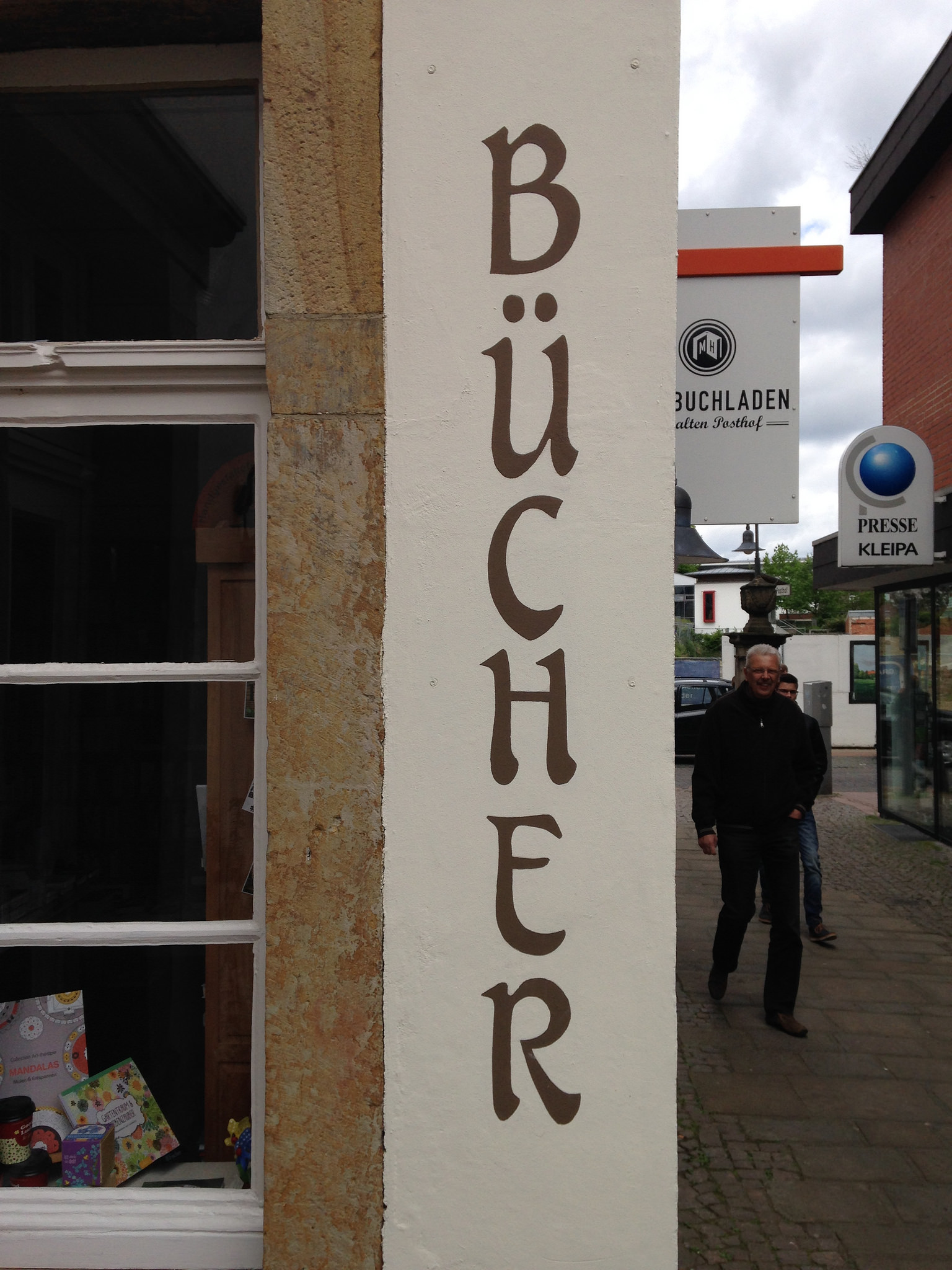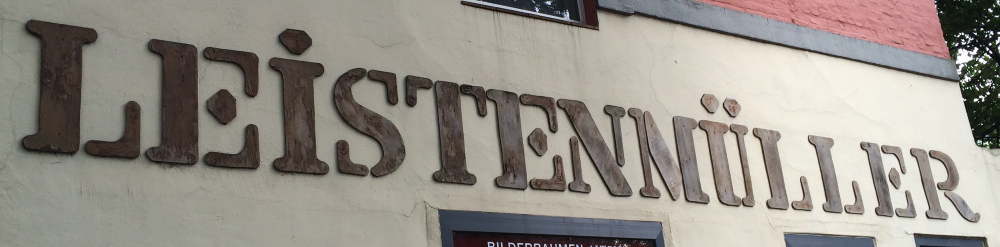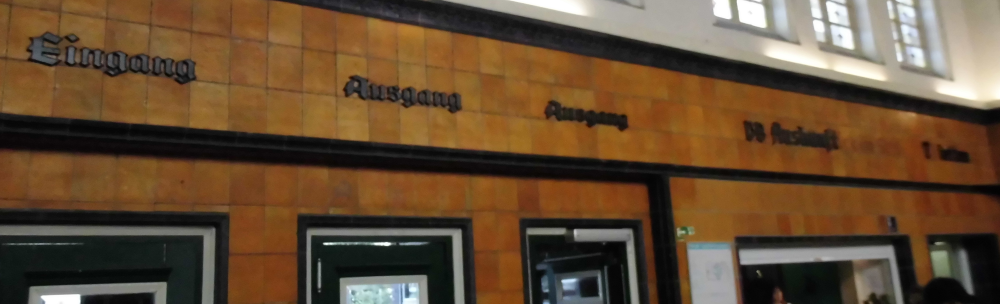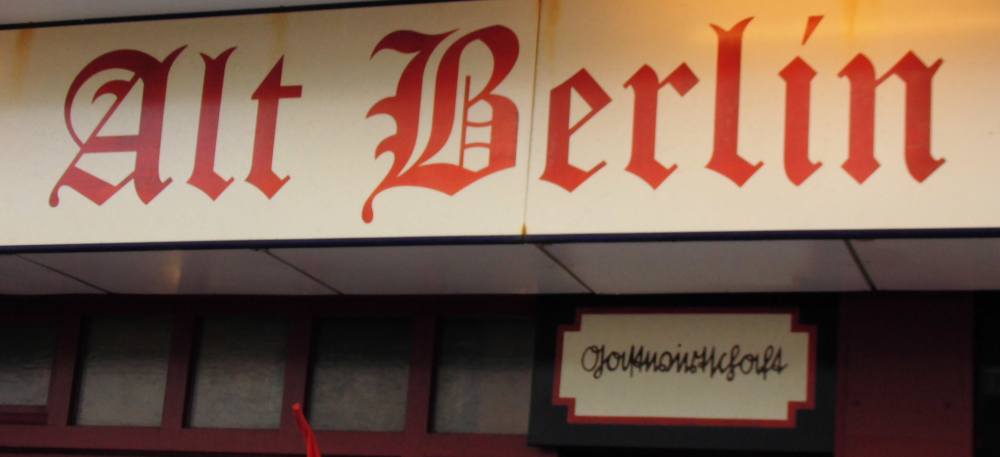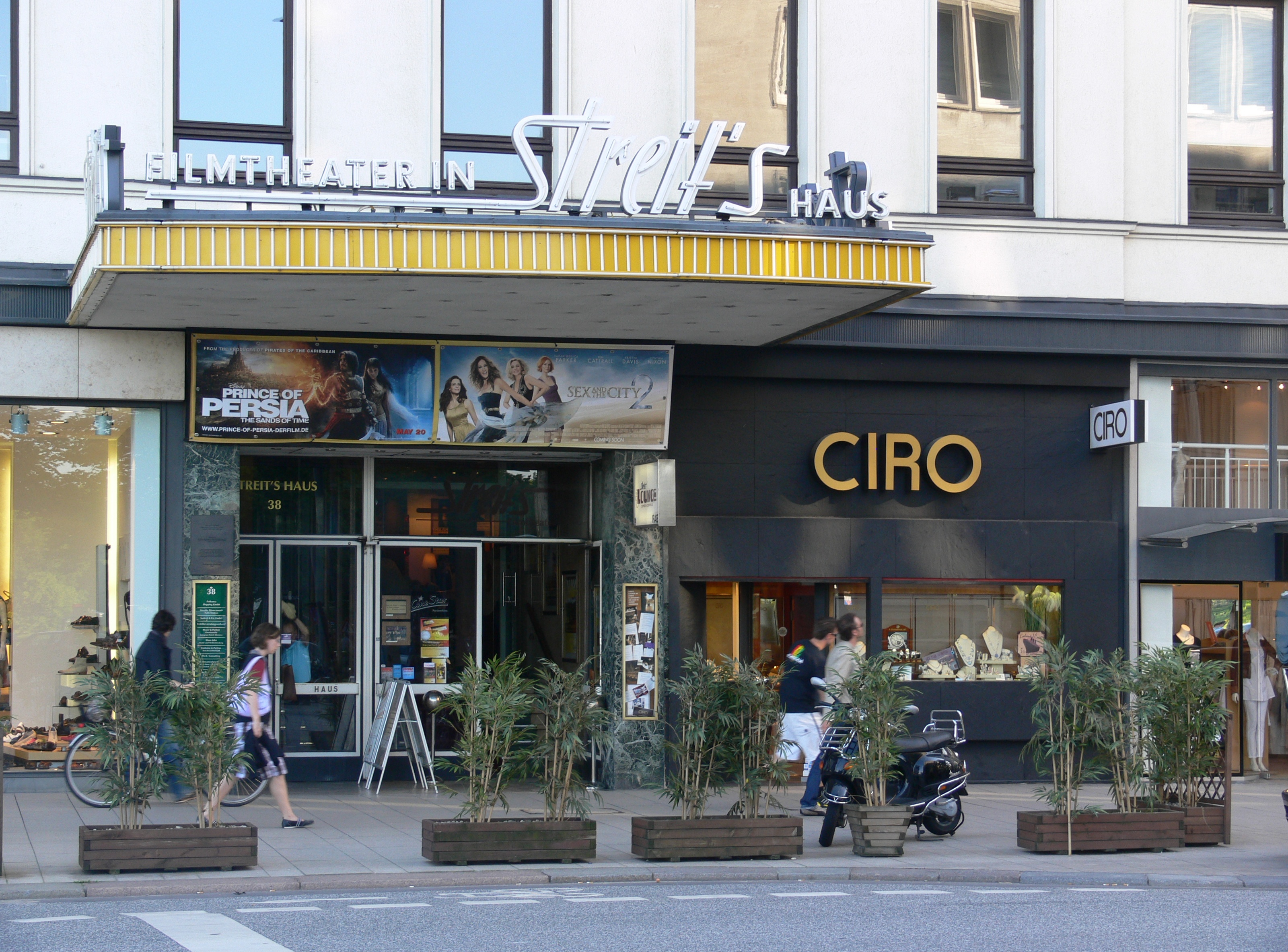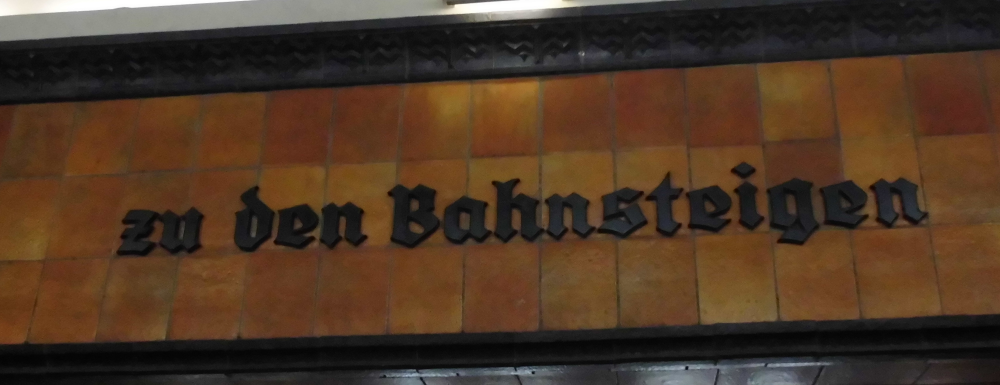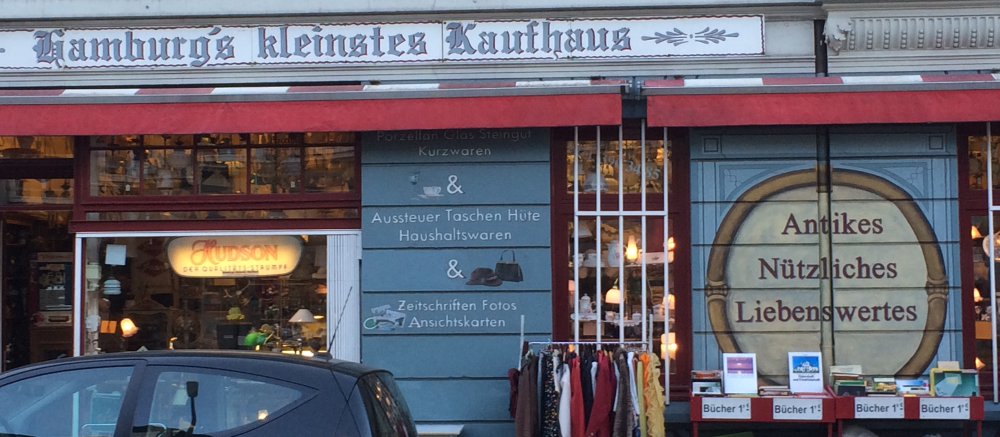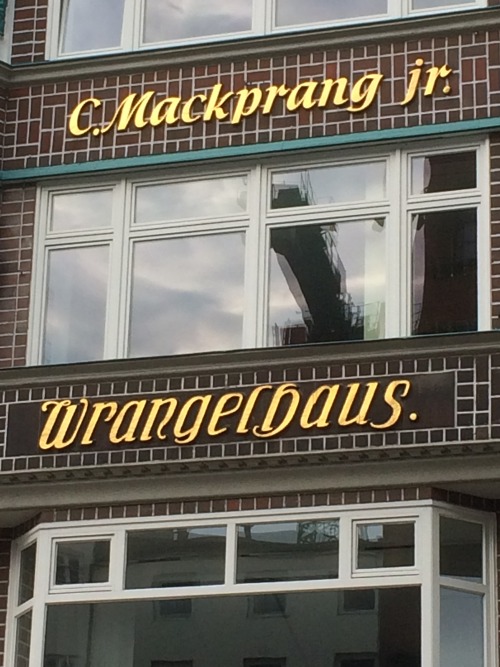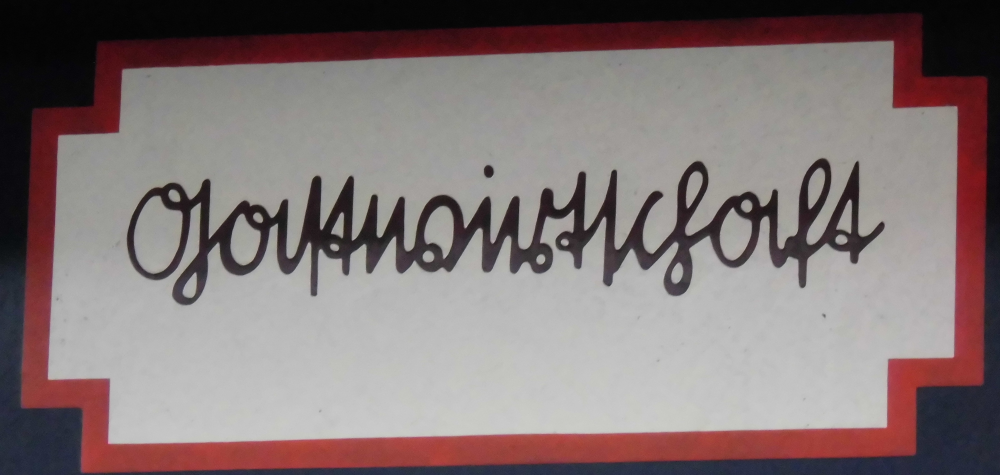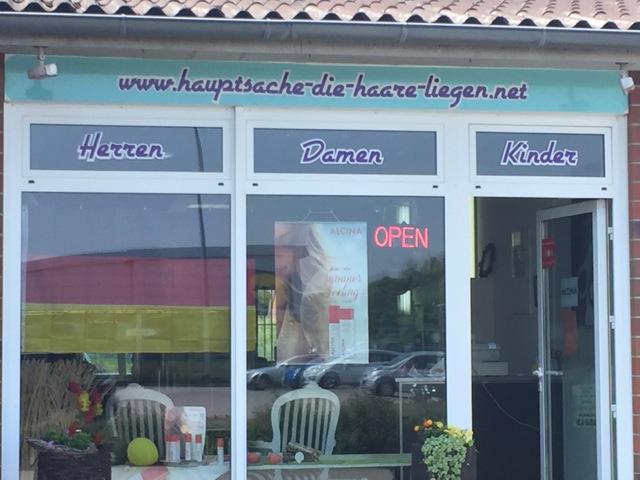
Und dabei sind hauptsache-die-haare-liegen.{biz|com|info} noch frei!
Da ich aber mit Domains (inclusive .net) so viel zu tun habe, hatte ich die Endung komplett ausgeblendet und wäre ohne Kathrins Hinweis nie darauf gekommen, dass sie die Bedeutung verändern könnte. Mir war nur der schöne (?) Beitrag im Wettrüsten möglichst lustiger Frisörnamen aufgefallen.
Schlau wiederum wäre es, wenn die Domainendung ein zweites t spendiert bekäme. Vielleicht hatten die Salonbesitzer ursprünglich diese Assoziation im Sinn? ;-)
Sogar mit Apostroph … ;-)
Stimmt auch wieder. Sieht aber trotzdem nett aus :-)
und "Hamburg´s kleinstes Kaufhaus" ist da schon richtig Kult. Kenne den Laden seit meiner Lehrzeit, auch mit den falschem Apostroph, der ja in Hamvburg lange Tradition hat, siehe Streit's Haus
Und als letztes für heute eine etwas andere Stencil:
Es kommt leider nicht so gut rüber, aber die Buchstabenteile sind aus Holz gefräst/gesägt/whatever und ca. 1,5cm dick.
Heute sehr gelacht in Mildstedt/Husum:
Interessant finde ich ja auch, dass der nur die Kinder zur Türe reinlässt.
Den Damen wird zwar "open" versprochen, aber sie scheitern, wie auch die Herren, an der Glasscheibe ...
Ähnliche hab ich kürzlich auch bewundert, nur mit aufgemalten Hilfslinien:
Als Südländer lese ich da auch: Hauptsache die Haare liegen nicht! Nun ja ... Dialektik ist schon was schönes ...